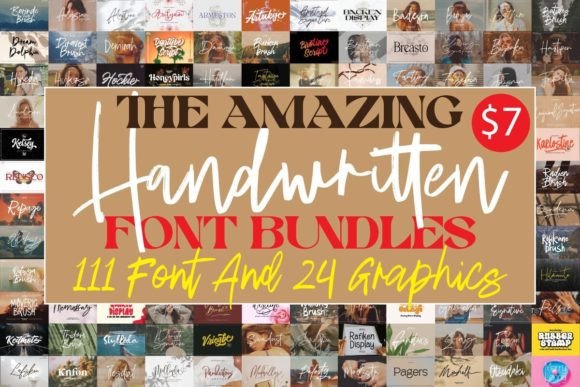
The Amazing Handwritten Font Bundles
Việc tìm kiếm các thành phần thiết kế phù hợp có thể là một thách thức, nhưng The Amazing Handwritten Font Bundles cung cấp một bộ sưu tập đặc biệt giúp nâng tầm công việc của bạn ngay lập tức.
Được chế tác với độ chính xác cao, The Amazing Handwritten Font Bundles cung cấp các vector sạch, kiểu chữ mượt mà và giấy phép thương mại để bạn yên tâm.